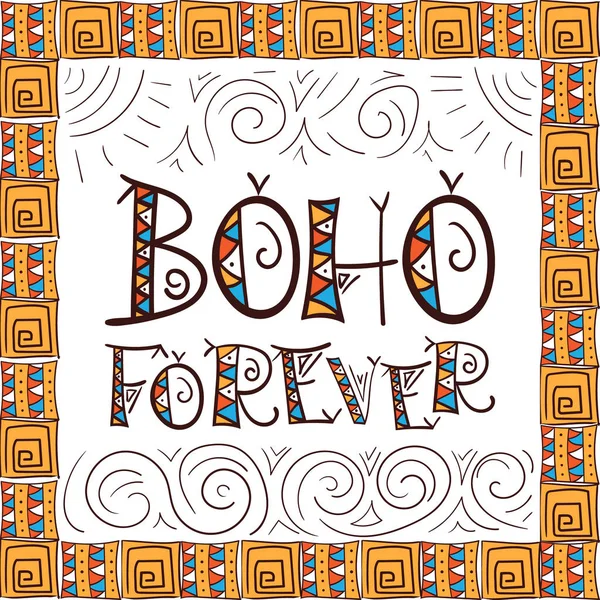
Архетипы в дизайне: как подбирать шрифты, графику и фотостиль | Публикации
Агентство Linii провело дизайн-исследование и составило рекомендации по работе с дизайном для каждого из 12 главных архетипов брендов
Про использование архетипов в брендинге написано огромное количество статей.
Они помогают классифицировать образы и поведенческие паттерны.
Впервые эту тему затронул психиатр Карл Густав Юнг. Впоследствии его труды переосмыслили и адаптировали для широкой аудитории, в том числе и для бизнеса. Сейчас выделяют 12 базовых архетипов брендов, активно применяемых в маркетинге и рекламе.
Команда агентства Linii в лице арт-директора Юлии Плотник и дизайнера Александры Янчуковой при консалтинге директора по стратегии Полины Васильевой провели дизайн-исследование и классифицировали каждый из 12 архетипов по нескольким категориям: шрифт, графика, палитра, фотостиль.
РодительАльтруист, которым движет сочувствие, щедрость и желание помогать
окружающим. Гораздо лучше заботится о других, чем о себе. Иногда не учитывает
чьи-либо реальные потребности, исходя лишь из своего мнения о пользе.
Типографика данного архетипа мягкая, обволакивающая, но не игривая. Аккуратные
собранные гротески с небольшими засечками без излишней размашистости с
умеренным или слабым контрастом.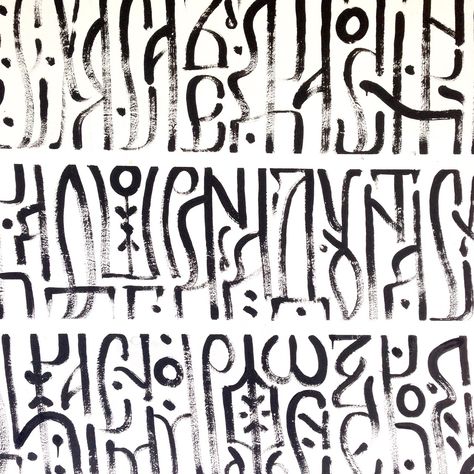
С точки зрения графики, у Родителя это могут быть плавные аккуратные элементы, создающие ощущение спокойствия и баланса. Для архетипа характерны природные, натуральные, растительные мотивы. Уюта может придать эффект потертости.
Для фотостиля типичны: мягкое освещение, естественность, теплые фильтры, соприкосновения фактур, передающие тепло и мягкость.
Цвета архетипа теплые, спокойные пастельные тона либо неконтрастные черно-белые.
Славный Малый
Убежден, что любой человек имеет значимость. Лишен невинной наивности и не ждет от жизни только добра. Умеет сопереживать и поддерживать. Хочет быть принятым в обществе и коммуницировать с другими.
В типографике Славного Малого не может быть никаких антикв, намеков на
засечки и какую-то претенциозность. Скругленные и понятные всем шрифты,
моноширинные без каких-то контрастов внутри букв, а также слега несовершенные
шрифты.
Графика Славного Малого тоже дружелюбна: какие-то геометричные формы или живые линии — овалы, круги, треугольники, чаще всего векторные формы без теней. Очень часто используются шейпы коммуникации, то есть там всякие мессенджеры, символы объединения и общения.